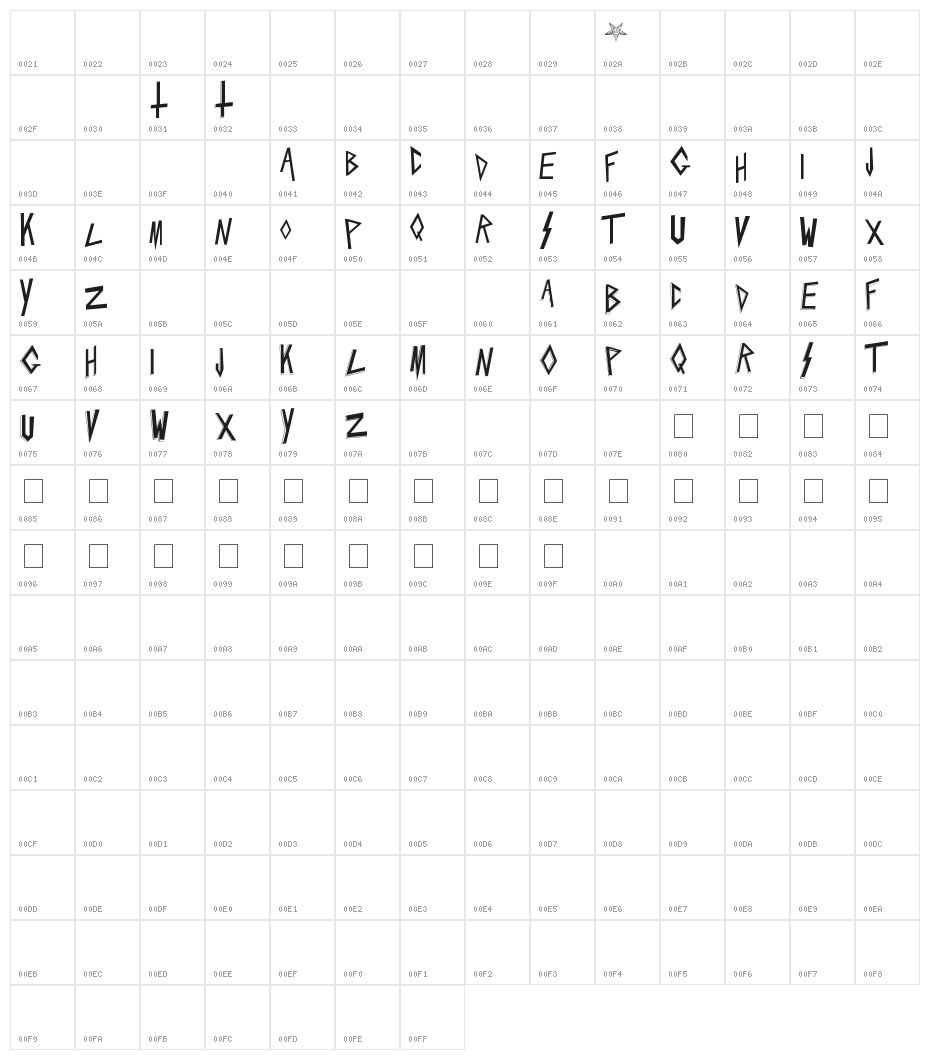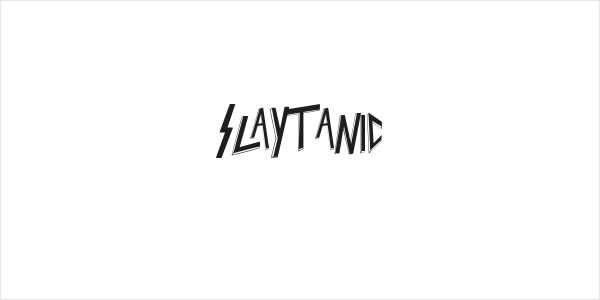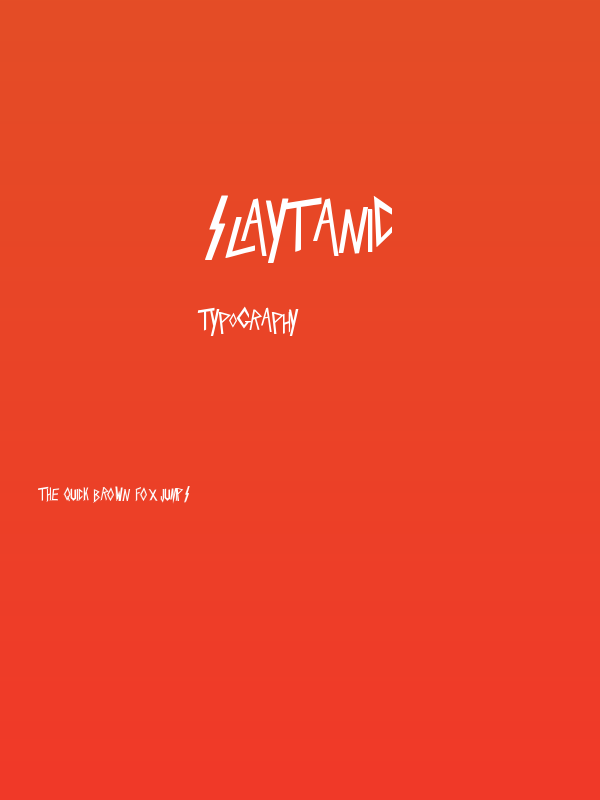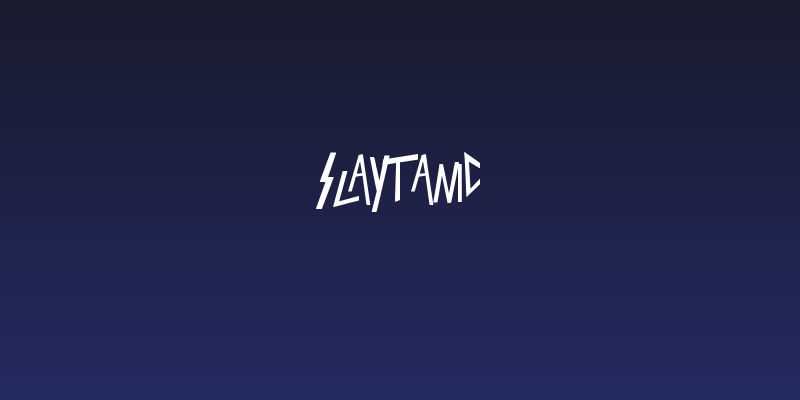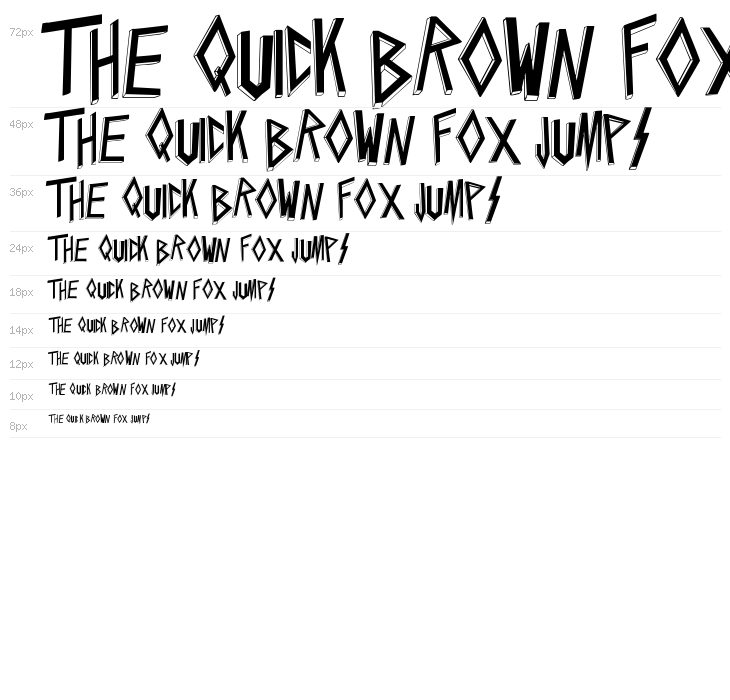
Slaytanic Font
| Stile generale | Modern, Decorative |
| Progetti proposti | Ideal for music album covers, band logos, event posters, and any project needing a bold, rock-inspired aesthetic. |